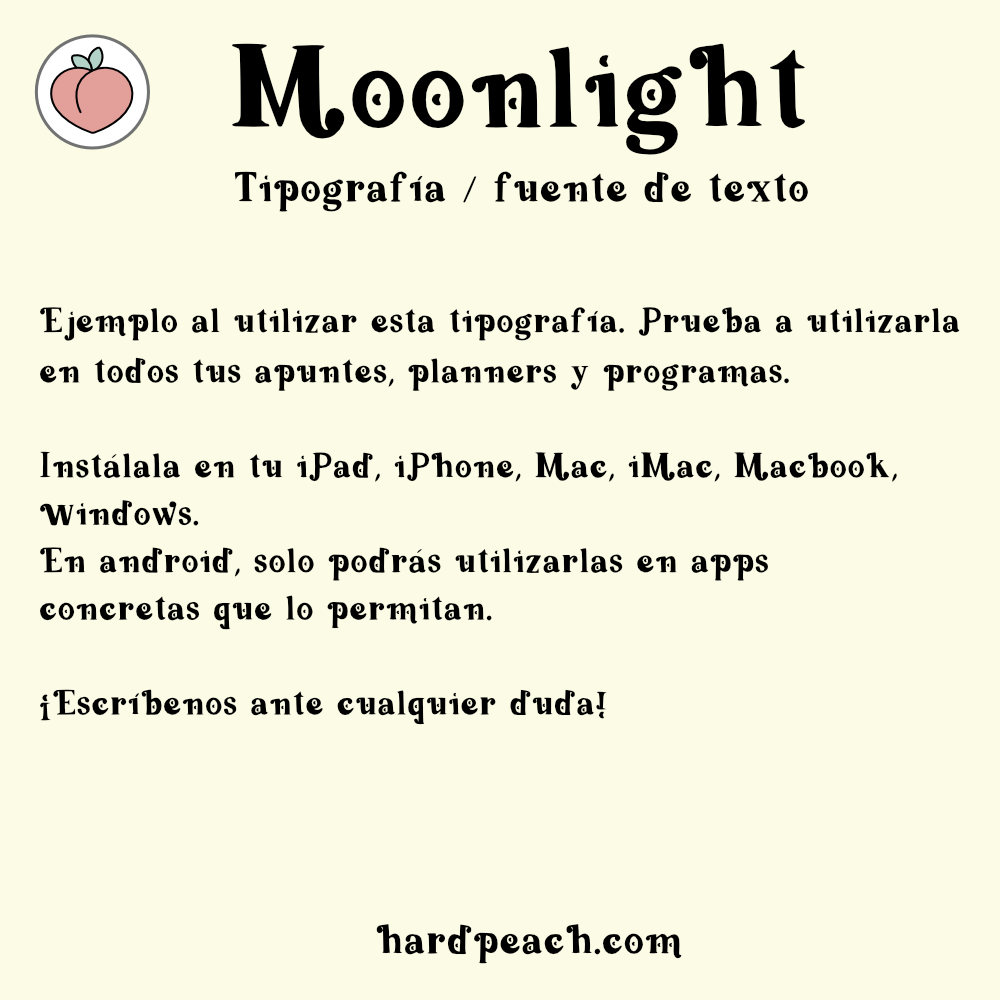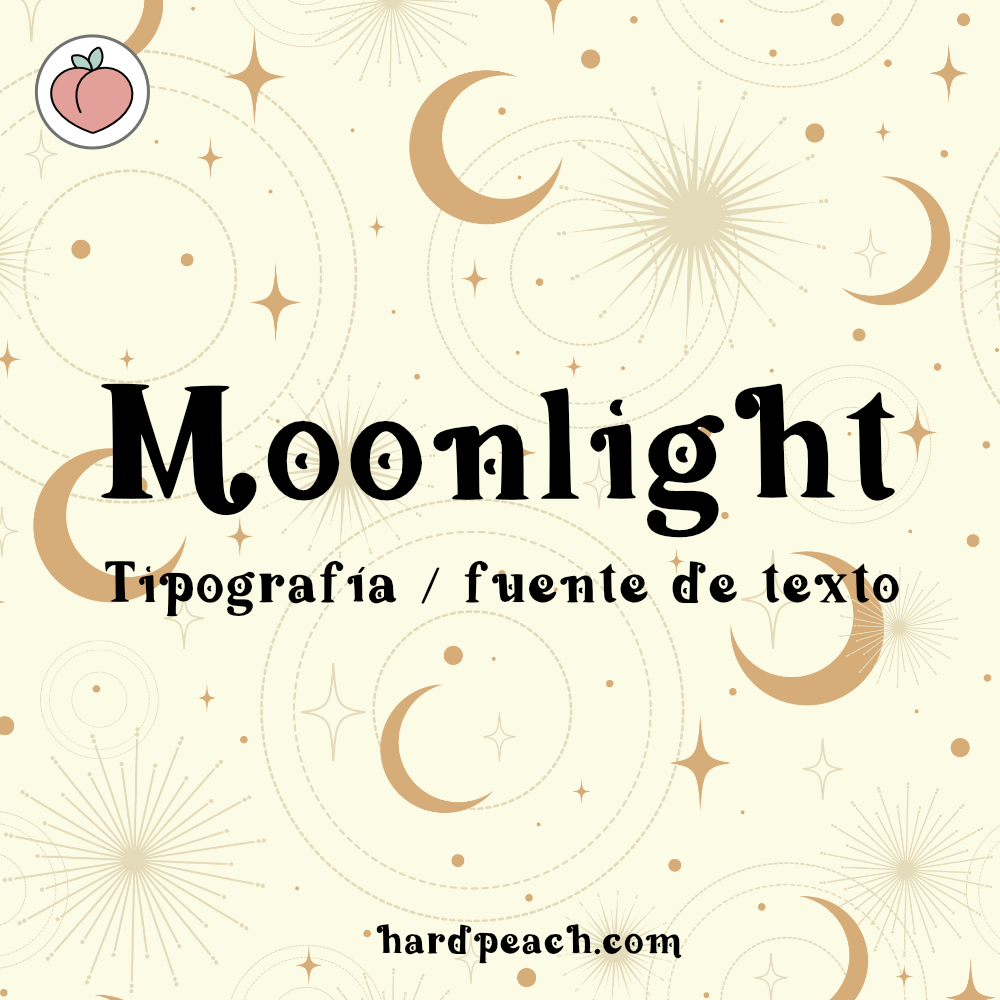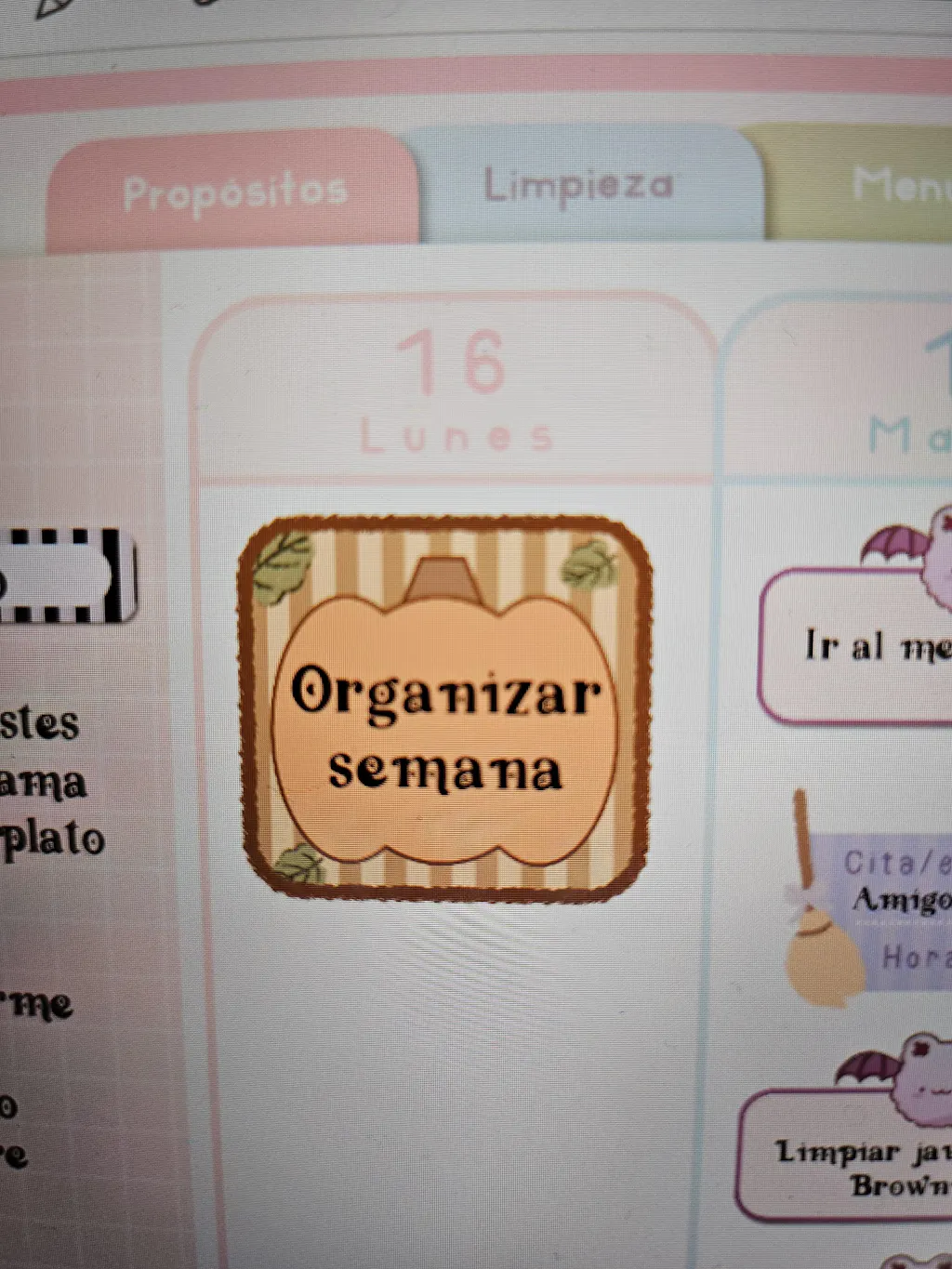
TIPOGRAFÍA MOONLIGHT: fuente moderna y elegante para títulos, encabezados y proyectos creativos
Descubre la tipografía Moonlight, una fuente moderna y elegante que podrás utilizar para títulos, encabezados, anotaciones y todo tipo de planes y proyectos digitales. Inspirada en la luz de la luna, Moonlight aporta un estilo único y sofisticado que hará que tus textos se vean profesionales y creativos.
Esta tipografía es perfecta para agendas digitales, apuntes, notas, proyectos de ilustración, diseño gráfico, presentaciones e incluso contenido para redes sociales. Su diseño versátil permite combinarla con otras tipografías para crear composiciones visuales armoniosas y destacar los elementos más importantes de tus trabajos.
Si quieres darle un toque profesional y elegante a tus títulos y proyectos digitales, Moonlight es la opción ideal para destacar y organizar tus ideas con estilo.
Esta tipografía incluye todos los caracteres principales, mayúsculas, minúsculas, números, vocales con tildes cerradas y abiertas y signos. Además de la letra Ç